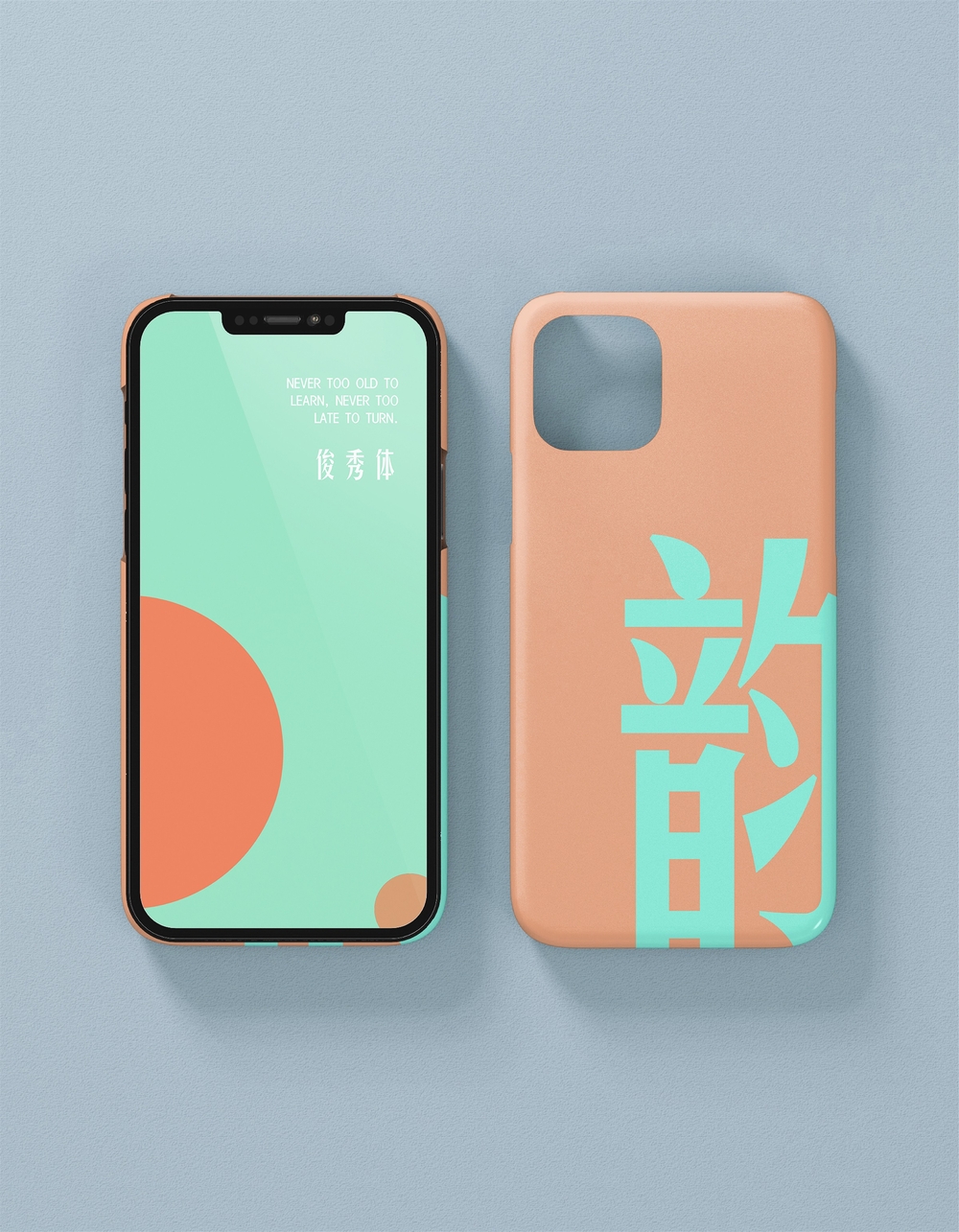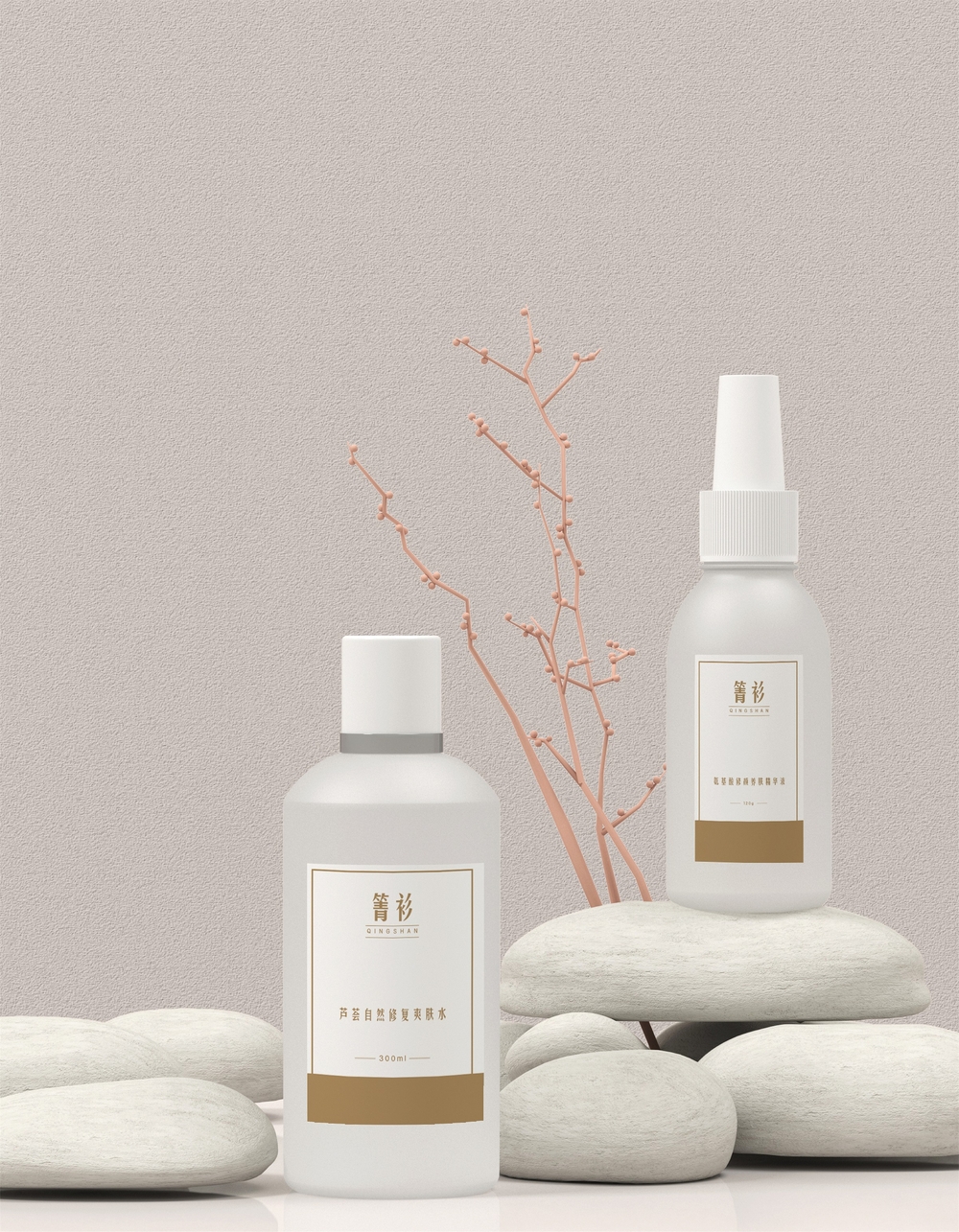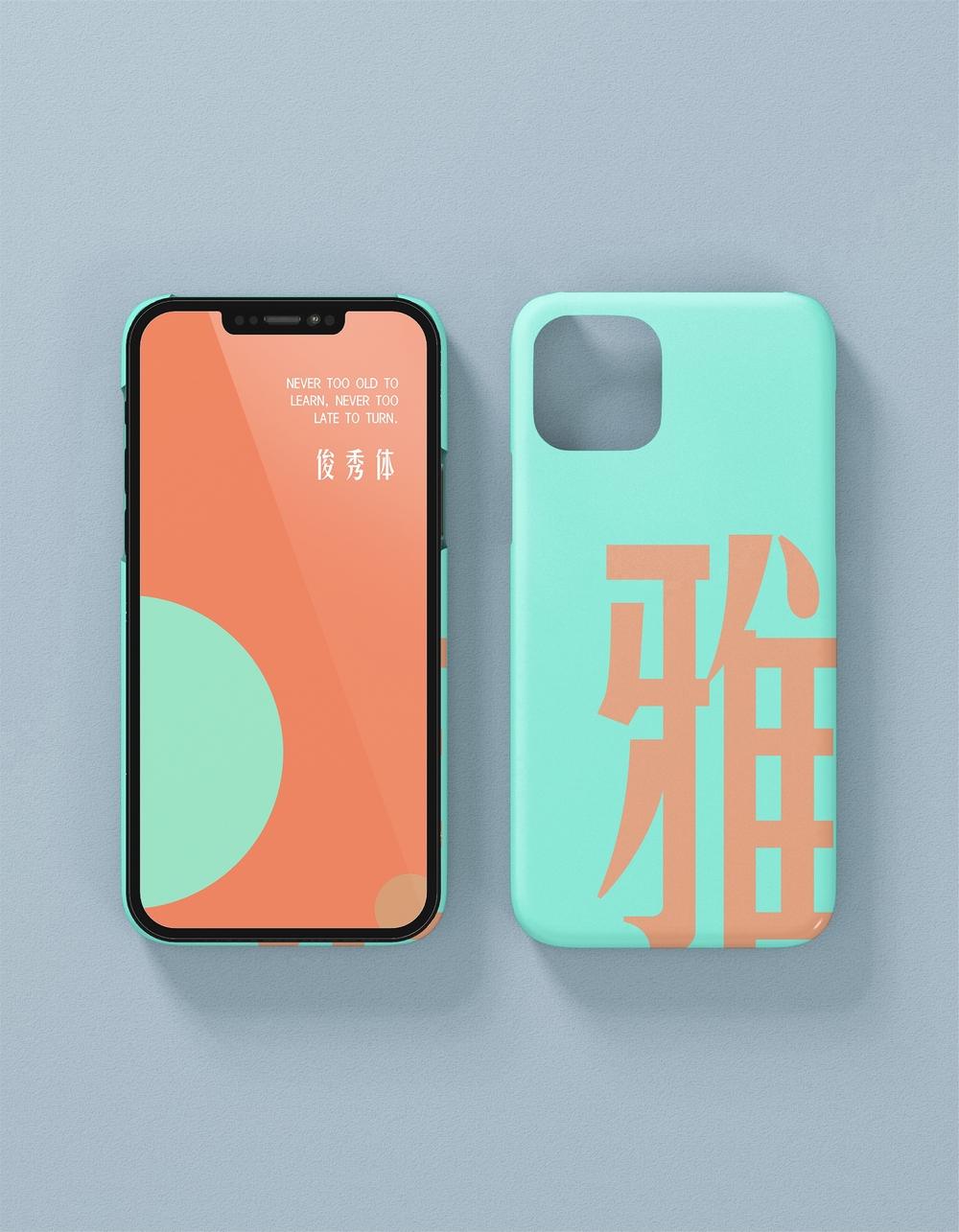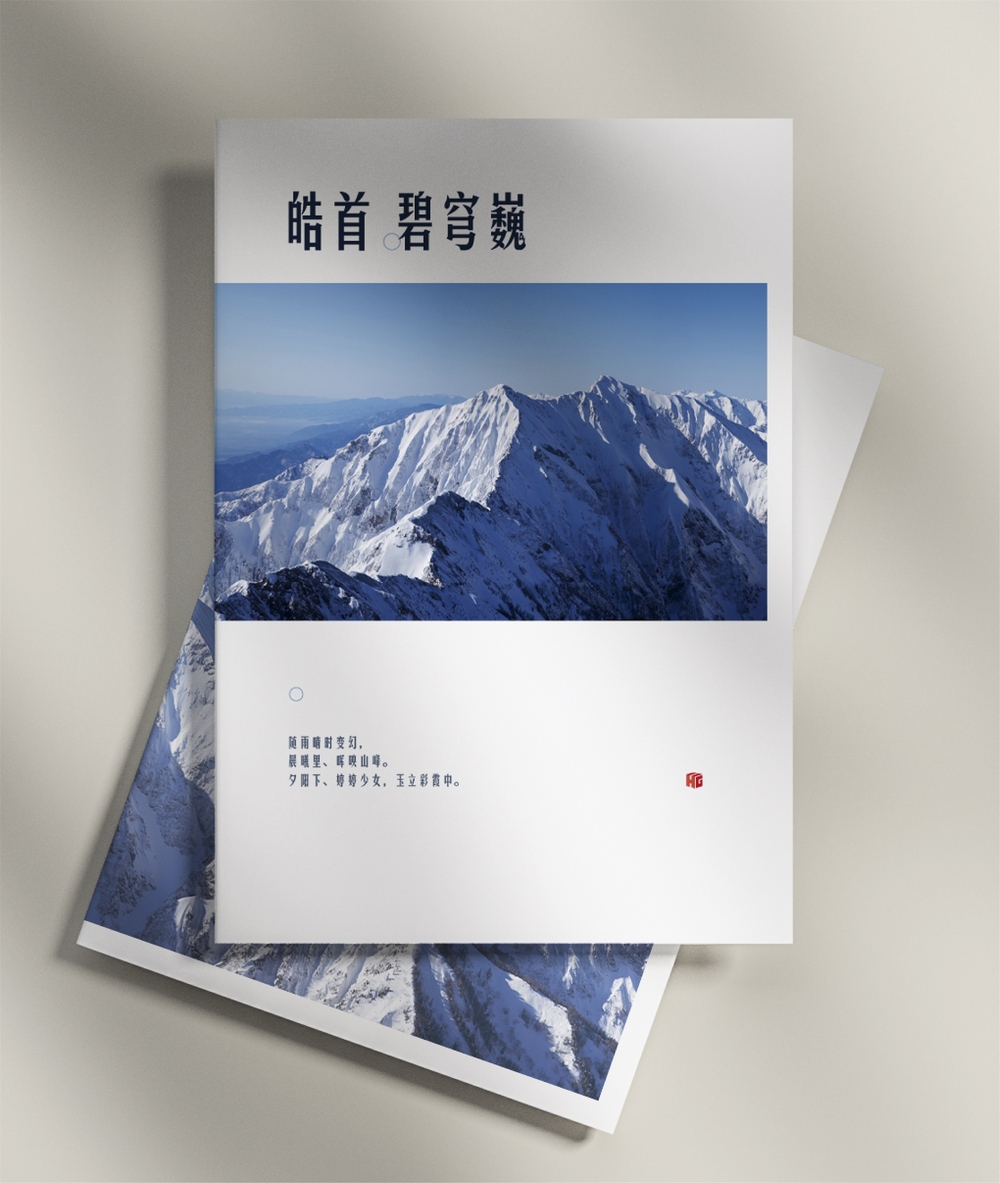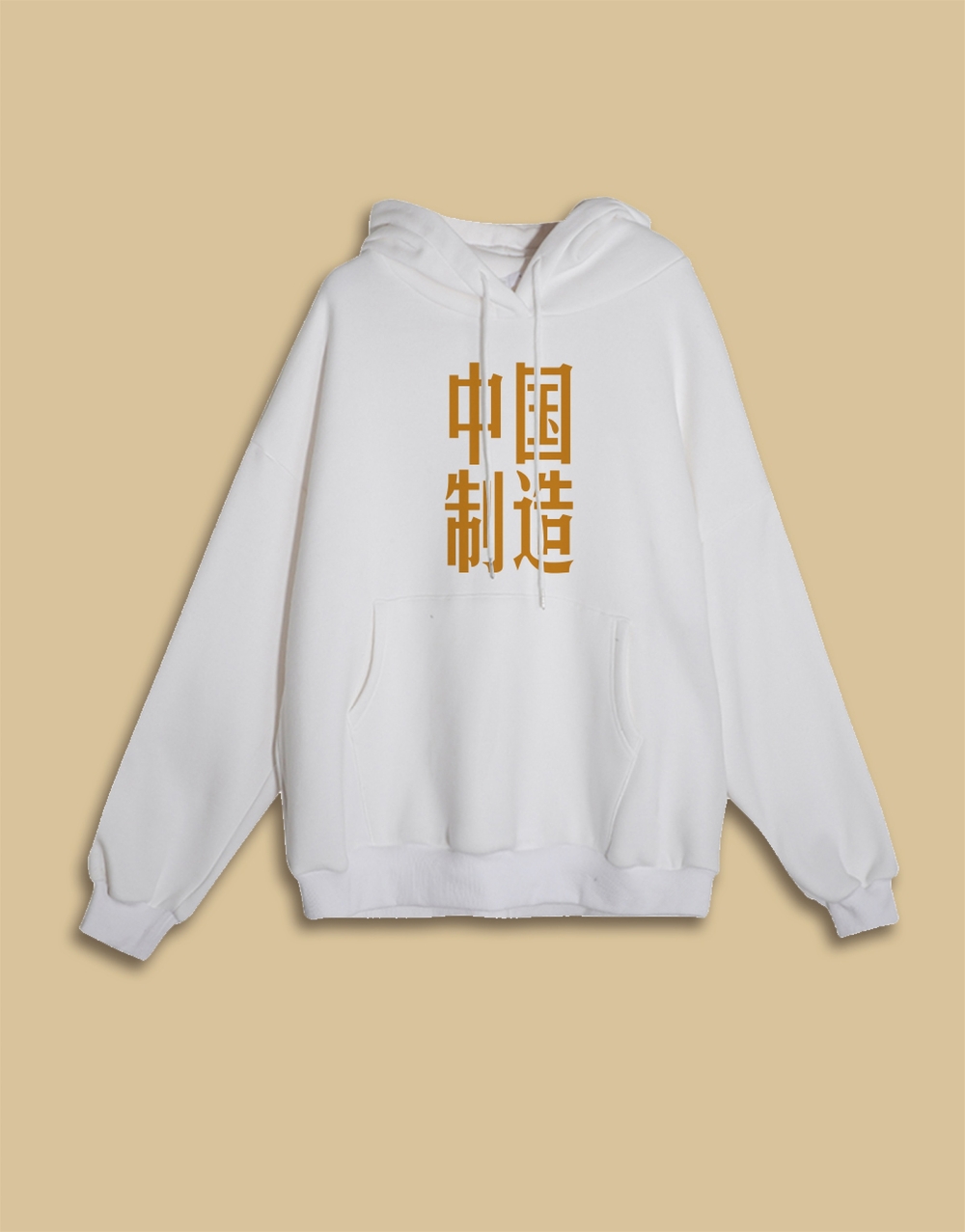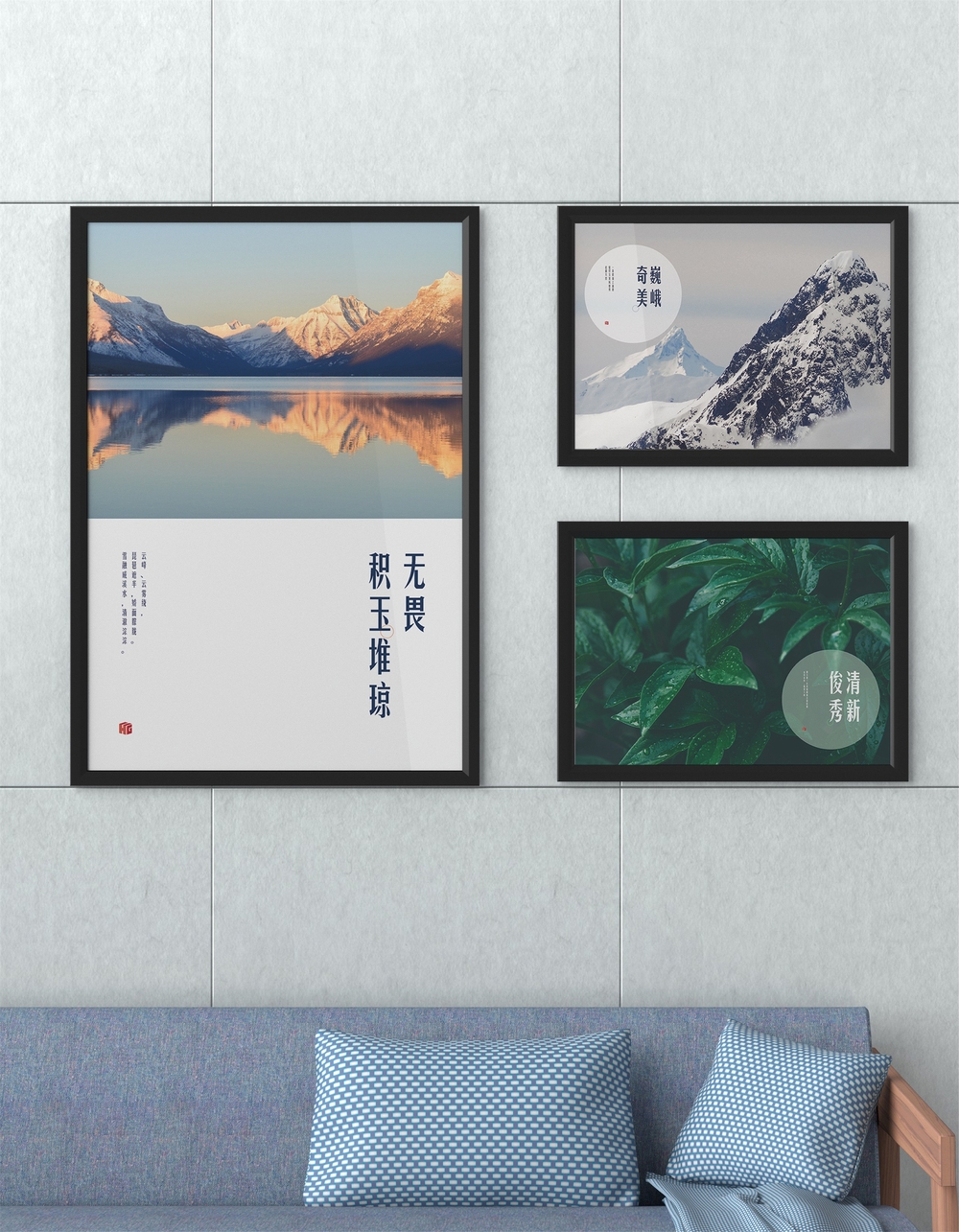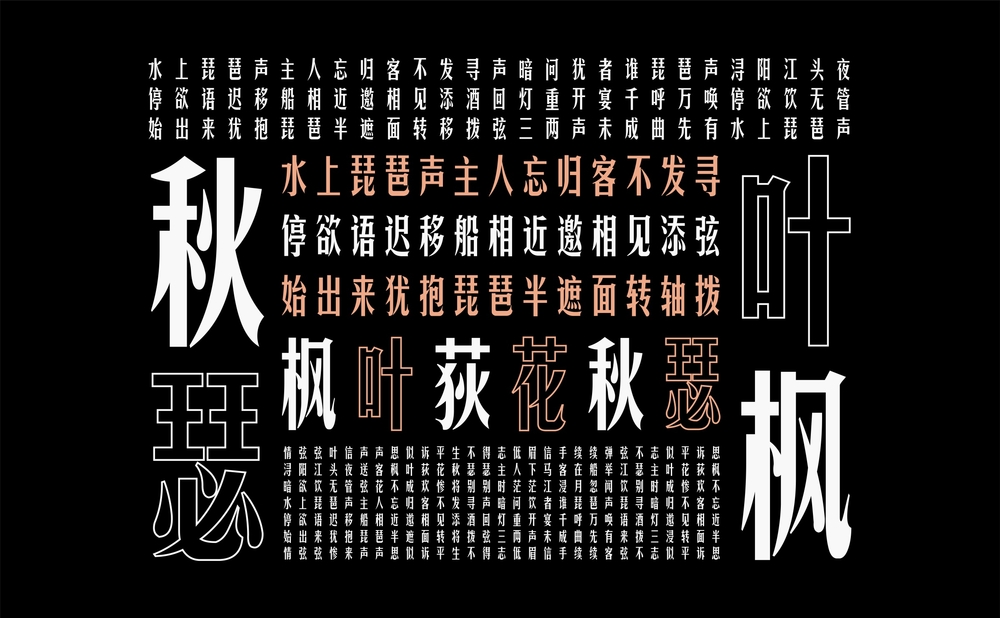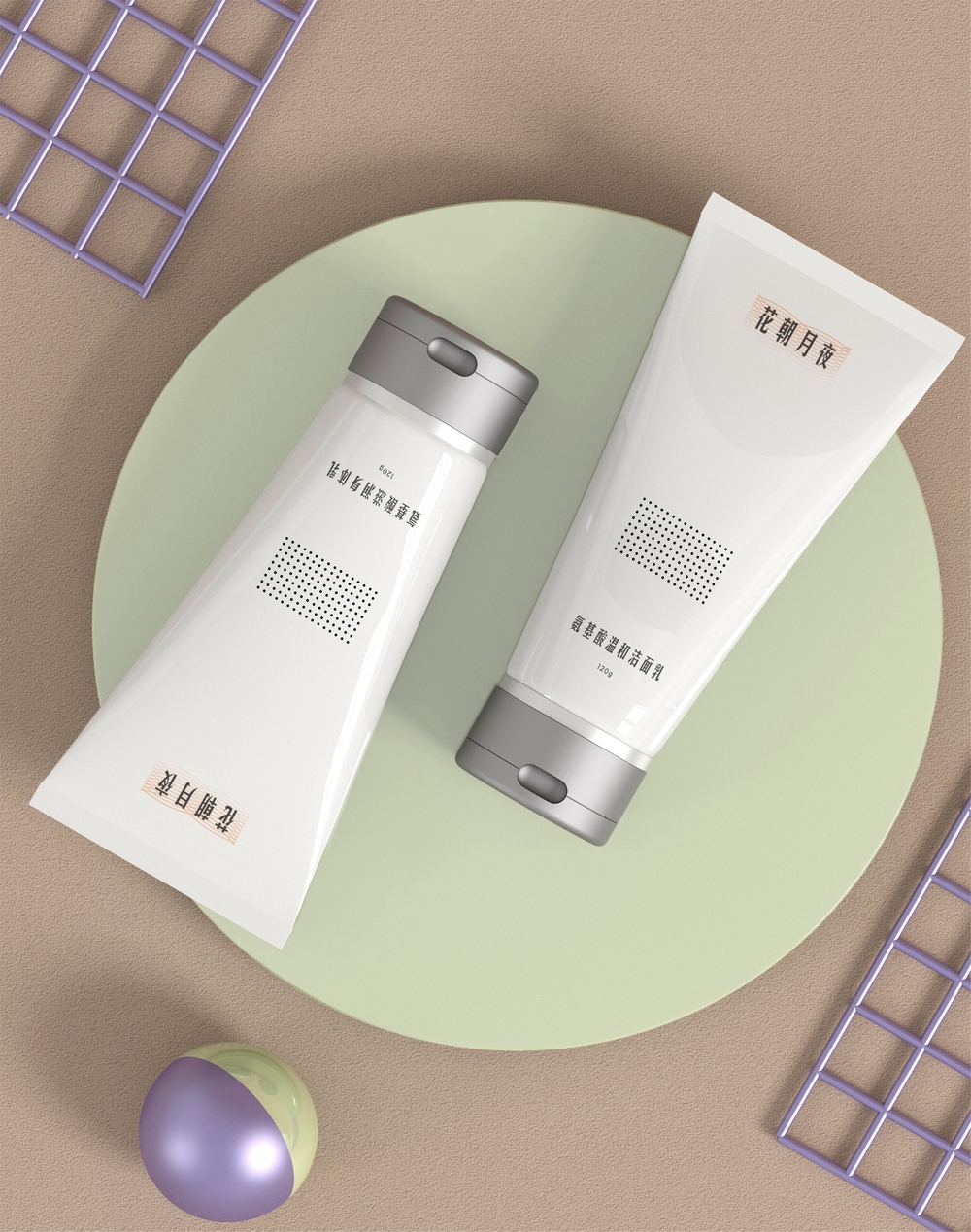
华光俊秀体
华光俊秀体,是华光首款免费可商用的字体,这款字体字形挺拔俊美,笔画刚柔并济,字体造型设计严谨并且充满了美感。
华光俊秀体是一款个性高挑、钢中带柔,应用范围广泛的中文字体,整体字形类似于宋体和楷体的结合变形,比例较为纤细修长。
这款字体适用于品牌形象、标志LOGO、广告招贴、书籍封面、娱乐、电商、影视、动漫等多种应用场景,尤其适合中国风设计的相关选题。